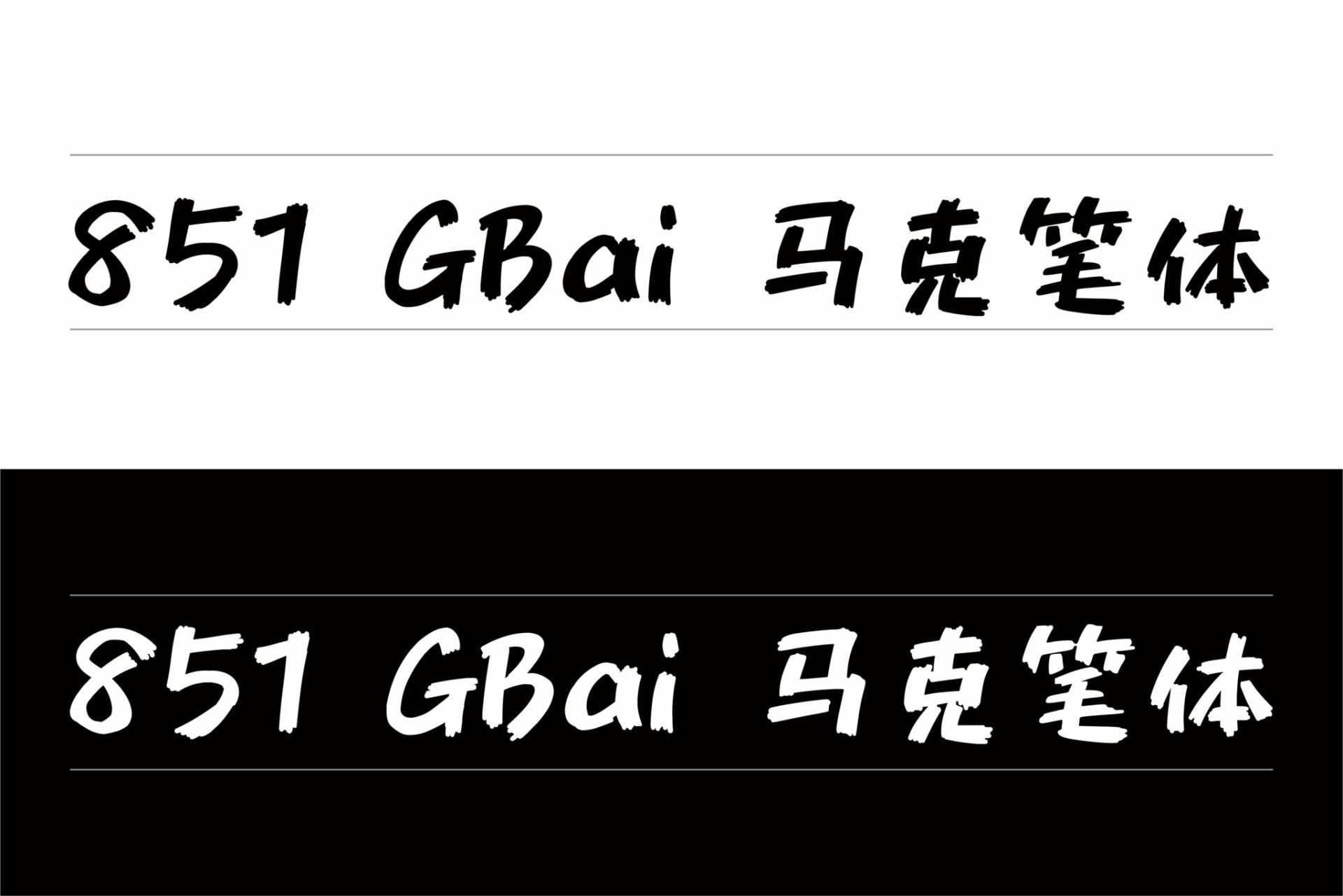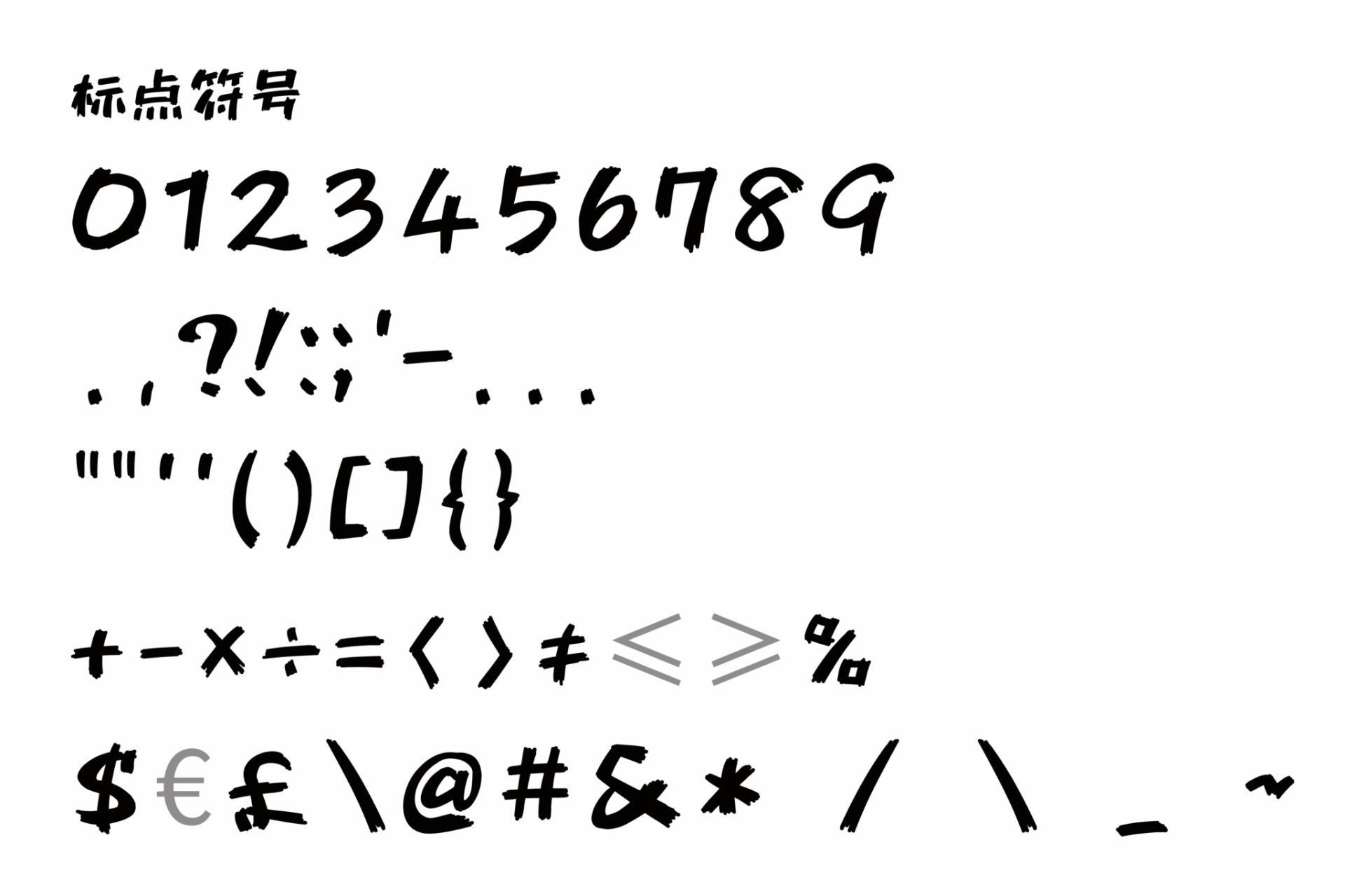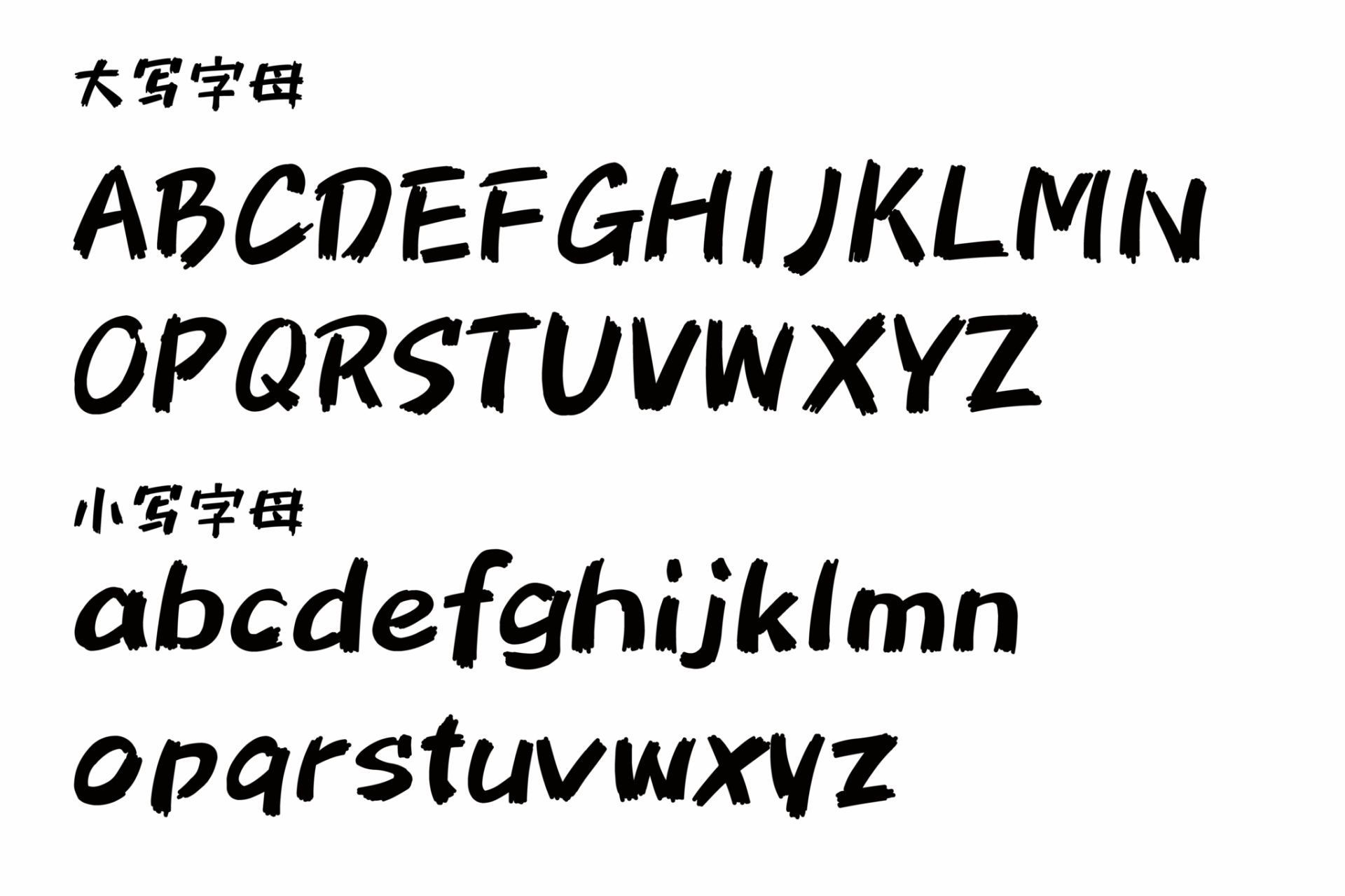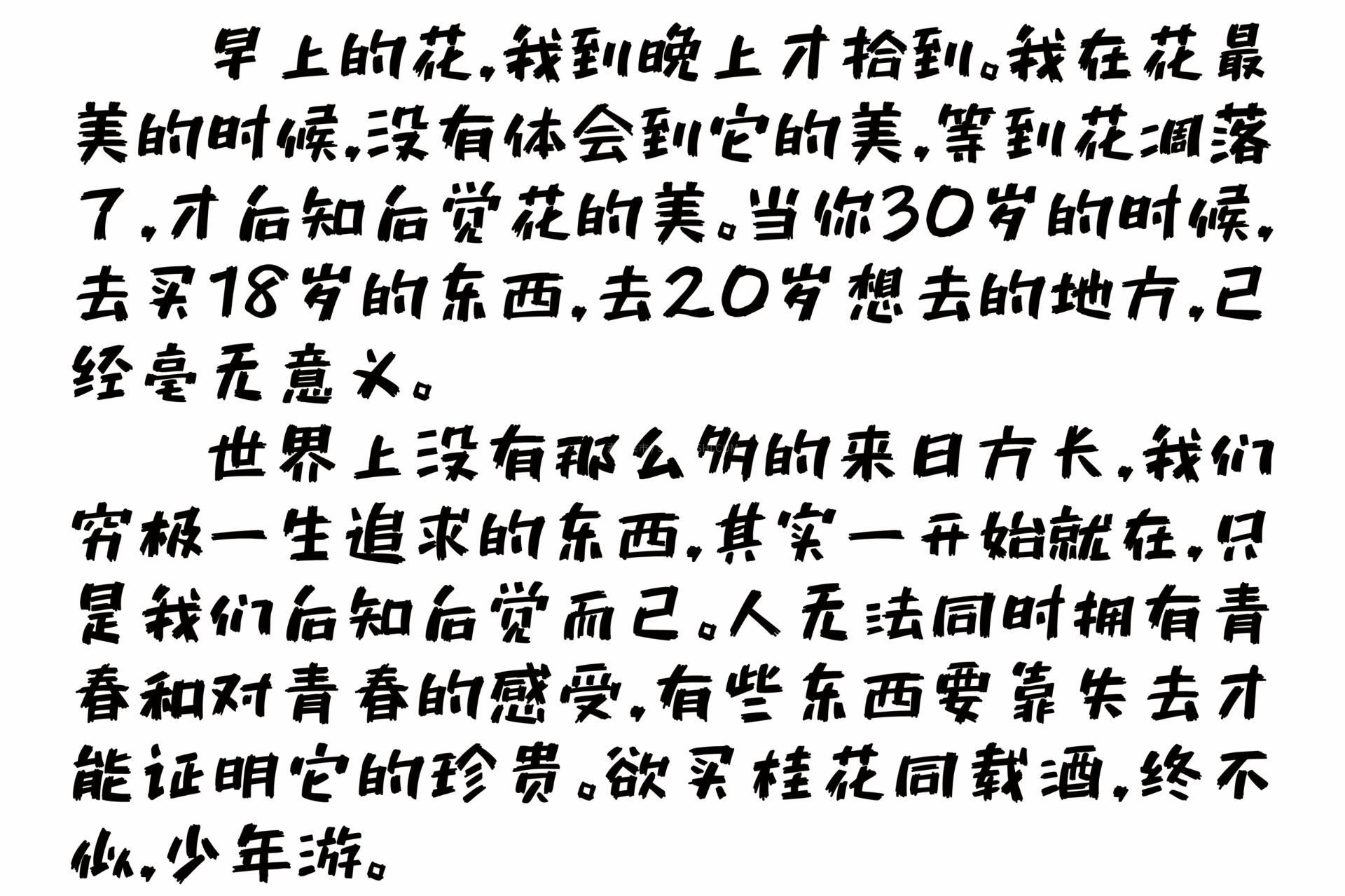
851 GBai 马克笔字体,免费可商用
851 GBai 马克笔笔体是由日本设计师 8:51:22 pm 原创设计的851チカラヅヨク-かなA字体,经由作者 lamda05 利用 zi2zi-jit进行扩展与汉化。高度拟真的马克笔书写质感。从字形展示可见,笔画边缘并非平滑的矢量路径,而是带有不规则的毛边、断续的飞白以及颜料渗透的厚重感,完美模拟了马克笔在纸张上快速运笔时的物理痕迹。风格圆润、随性且可爱,但在原生状态下仅支持日语汉字。